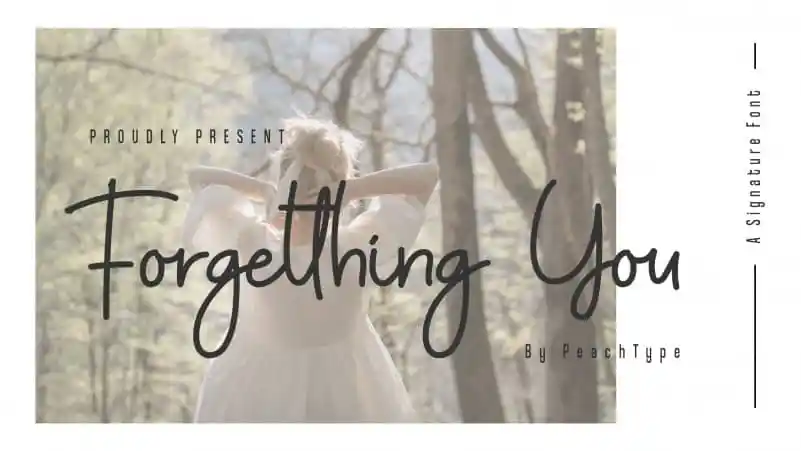
Forgetthing You Handwritten Font – Download Grátis
A Fonte ‘Forgetthing You Handwritten’ é uma escolha inteligente para aqueles que buscam uma mistura de sofisticação e autenticidade no seu trabalho gráfico. Esta fonte, criada pelo designer beacon, oferece um estilo elegante e natural, perfeitamente adaptado para aplicar em designs de letra careca. Ela tem a habilidade única de dar ao seu design um toque inconfundivelmente pessoal, como se fosse escrita com a própria mão. Perfeito para incluir mensagens emocionadas num quote ou qualquer outro uso criativo, este estilo único e autêntico irá reforçar cada projeto que você criar. Seja você apresentando um sentimento de amor incondicional ou simplesmente querendo manter uma lembrança especial do seu trabalho em uma fonte cuidadosamente escolhida, ‘Forgetthing You’ certamente fará a diferença. Não hesite em explorar sua versatilidade e profundidade ao fazer download desta fonte incrivelmente única.